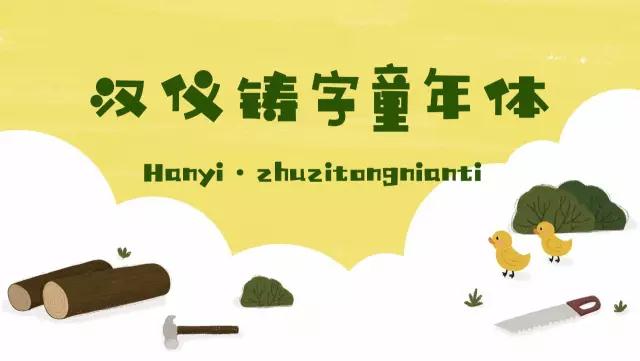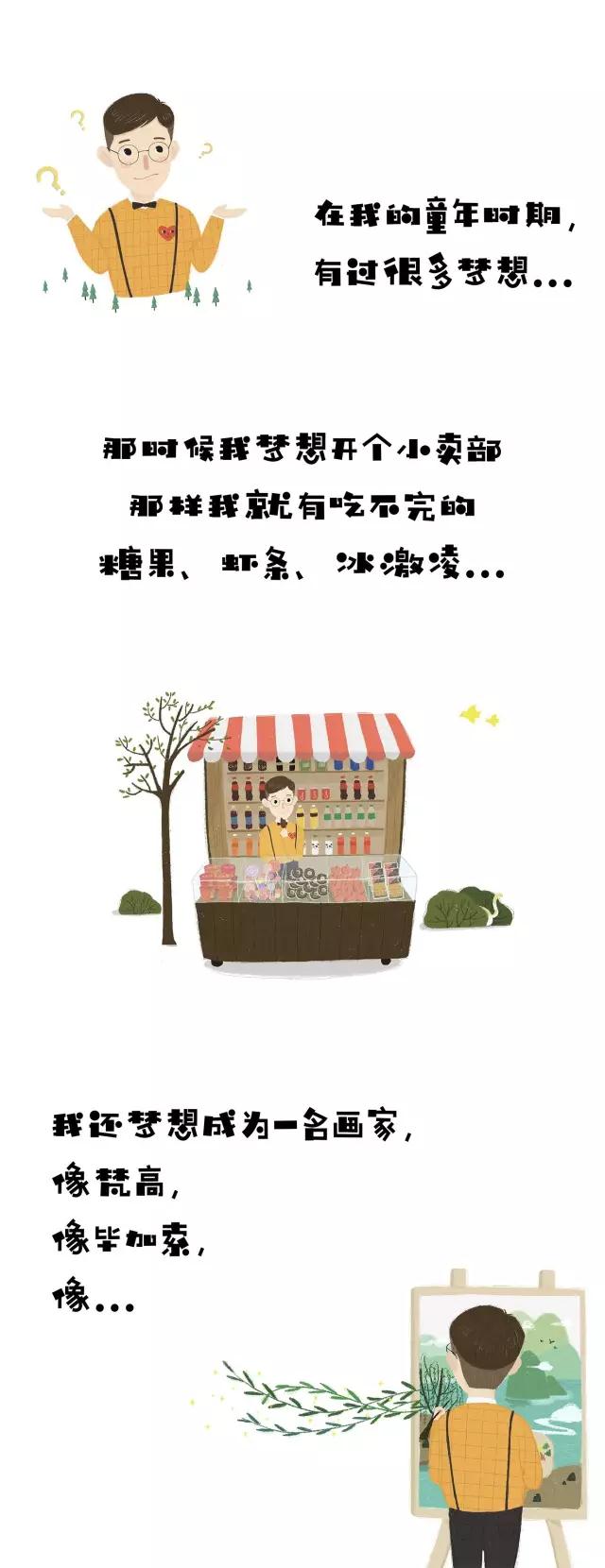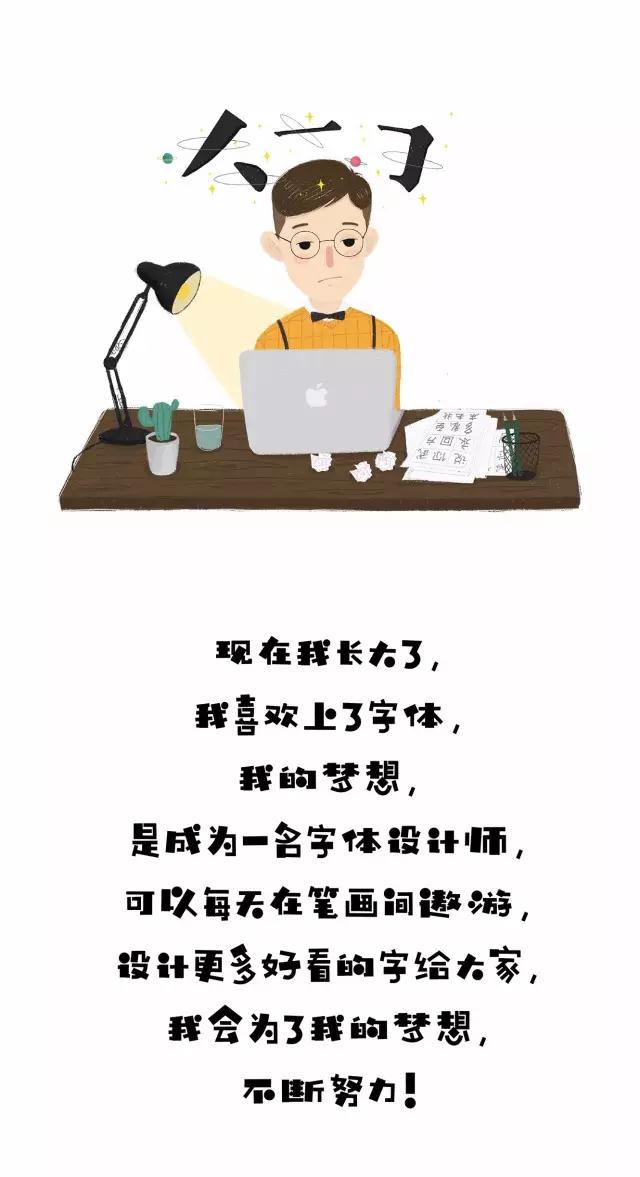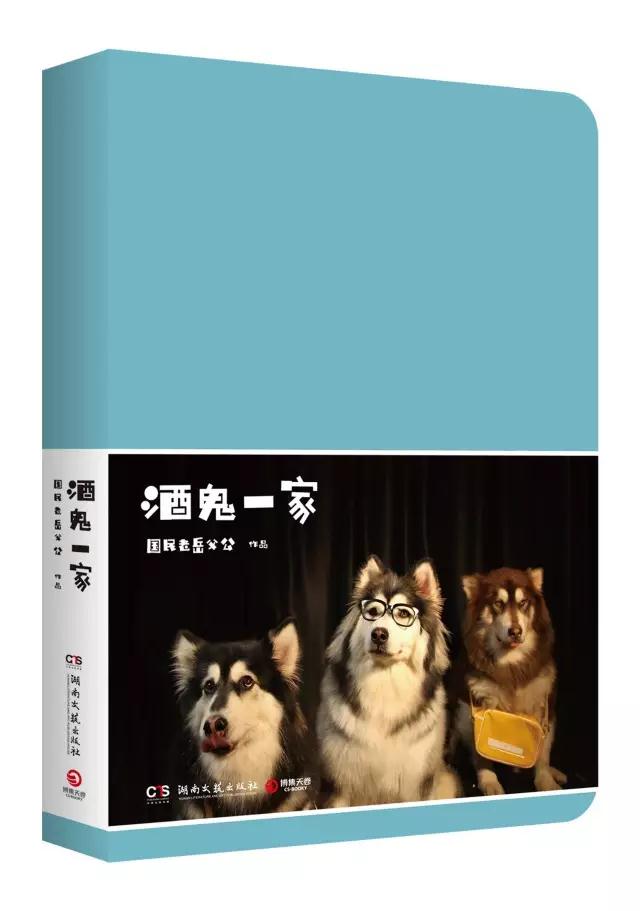
汉仪铸字童年体介绍、字体案例,9 款儿童节标配字体
距离“ 6.1 ”儿童节还有15天,
是的,
你还有两周的时间去完成儿童节的设计,
汉仪新品——汉仪铸字童年体
+9款儿童节标配字体
今日正式上线!
字有童心,
搭乘汉仪童年时光机,
一起织造童年!
汉仪铸字童年体
合作工作室:铸字精舍
中文简繁及网络常用字9169+符号664
字体特征解读
【立意活泼,追求趣味】
横竖粗细对比强烈,笔划中加入圆形作为辅助,使这款字体显得更加活泼生动。
【趣味组合,笑口常开】
“口”的左上方做开口的处理,在易识别的情况下,笔画间的灵活搭配更突显字体的趣味性。
【风格统一,重心一致】
在笔画统一,粗细均衡的基础上,字与字之间达到了视觉中心的统一 。
【笔画生动,个性鲜明】
笔划特点生动,个性鲜明,横竖没有绝对的横平竖直,少了普通黑体的古板,多了几分活泼俏皮。
字体应用展示
绘本字体《我的梦想》
字体应用展示
微博第一尴尬段子手:国民老岳父公
作品《酒鬼一家》封面字体